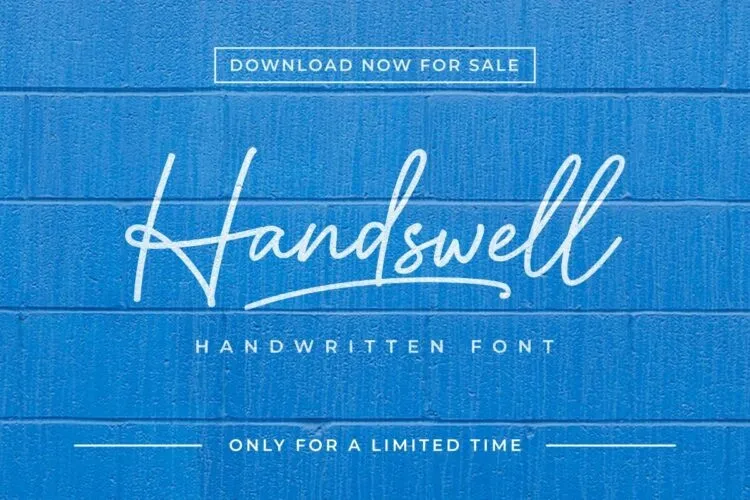
A fonte Handswell é uma elegante escolha para aqueles que desejam adicionar um toque delicado e natural a seus projetos de design. Esta tipografia monoline script, com suas linhas sutis e traços finos, parece ser o resultado da mão humana, oferecendo um ar de feminilidade e elegância ao mesmo tempo. Ideal para qualquer tipo de projeto visual, desde uma marca forte até cartões de visita minimalistas ou camisas criativas, a Handswell traz um estilo único que combina naturalidade e personalização. É perfeitamente adequada tanto para textos como para elementos gráficos, como logotipos, slogans ou qualquer outro conteúdo visual. Seja você designer de publicidade, de moda ou apenas alguém buscando dar um toque especial a suas criações, a Handswell é uma opção ótima para tornar seus projetos ainda mais interessantes e memoráveis.